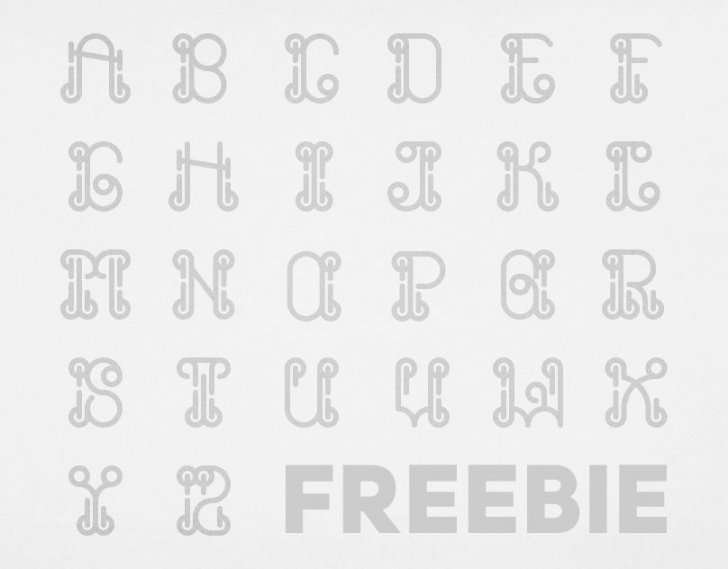
飾り付きのベクターフォント(商用可)「Free Vector Font: Kurt」 2019.03.24 2016.10.06Free Vector Font: Kurtは、飾り付きのベクターフォントです。AI, EPS形式のベクターファイルです。ポスターや看板など、大きなサイズでの使用に適しています。無料でダウンロードできて、商用利用可能です。